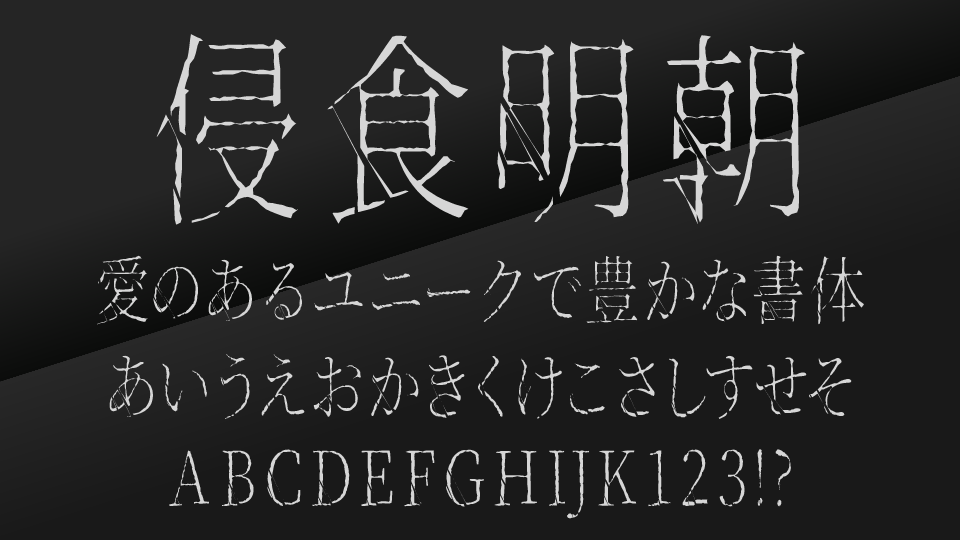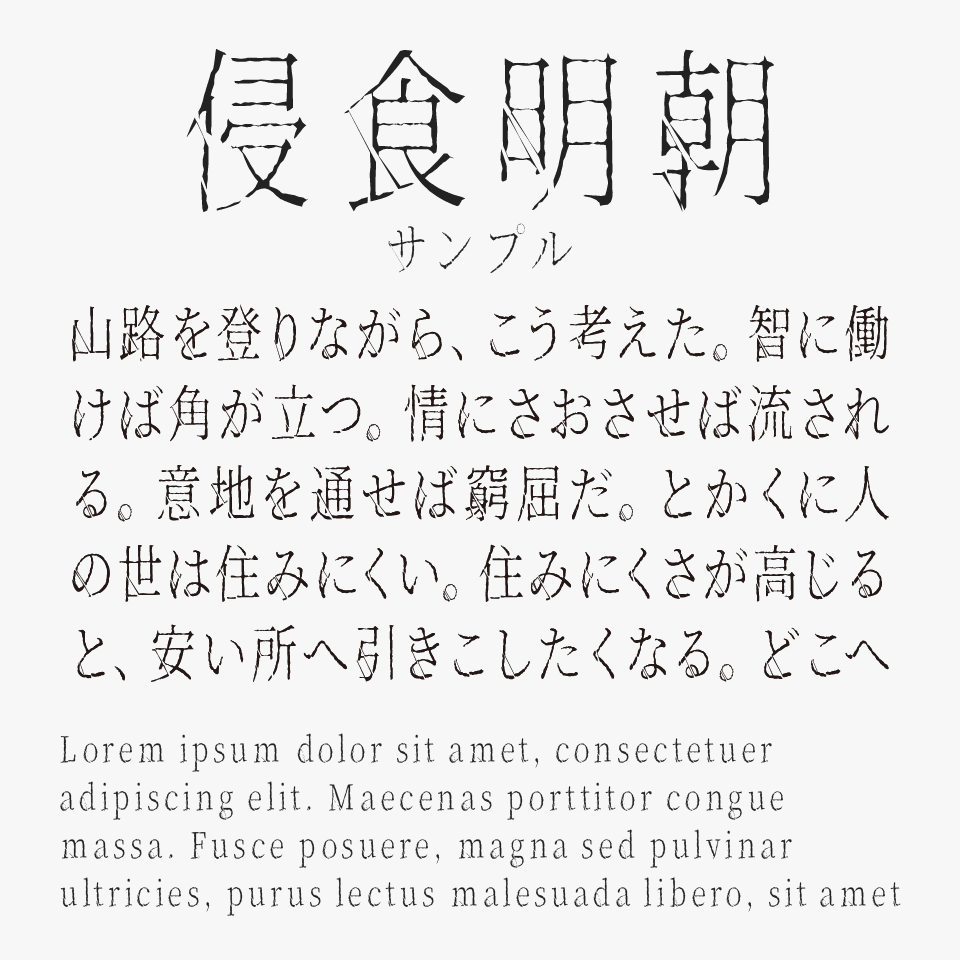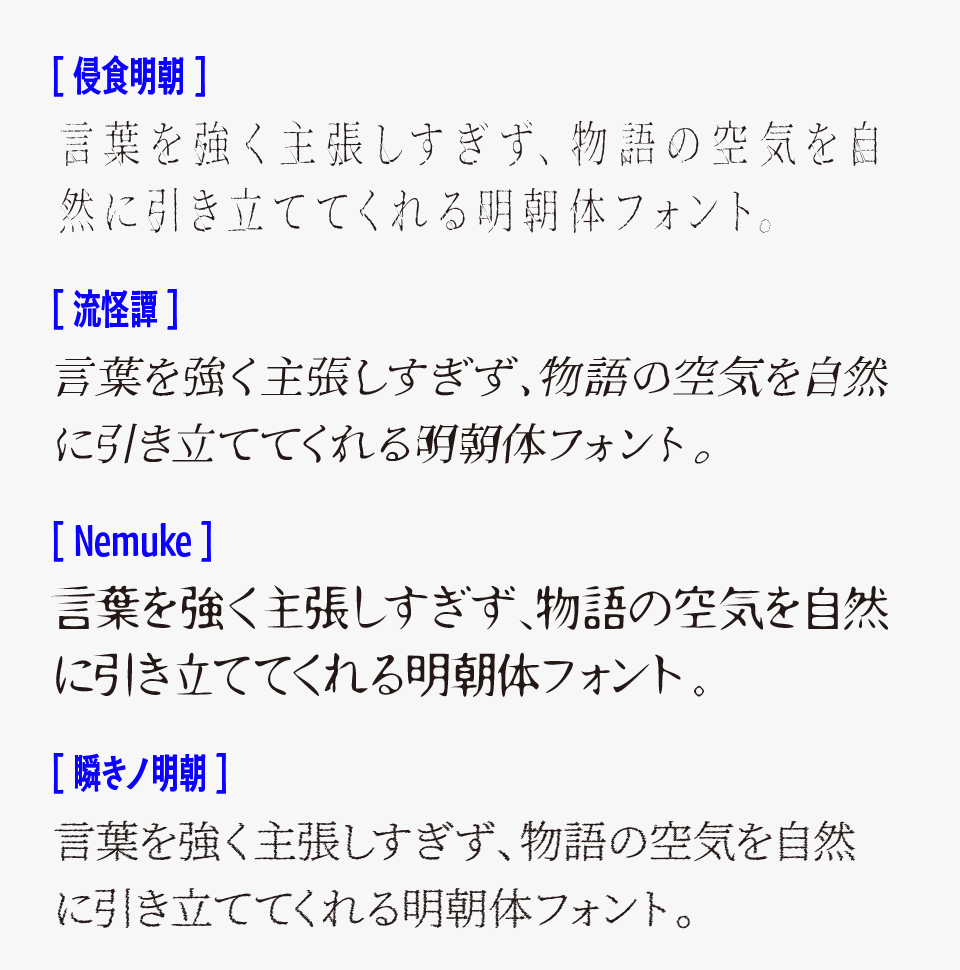
侵食明朝フォントは、源ノ明朝をベースに全体をやや長体に調整し、随所に亀裂を入れていることで、蝕まれて侵食されている雰囲気がある明朝体です。
繊細でシャープな骨格が持つ上品さと、侵食されたようなノイズ感が絶妙で、美しさの中に退廃的でダークな空気を感じられるフォントです。静かな恐怖感や異質さを演出できる、非常に個性の強い明朝体フォントです。
幻想的で不穏な世界観を演出しやすく、ホラー作品のタイトル、ゲームUI、ダークファンタジー系のビジュアル、小説表紙、MVデザインなどにぴったりなフォントです。
侵食明朝
侵食明朝フォントを、ほかの不穏さや異質感を表現した明朝体フォントと比較してみると、“文字そのものが侵食されていくような破壊的なデザイン表現”が特に印象的なフォントです。
比較フォントは、「流怪譚」「Nemuke」「瞬きノ明朝」を使用していますが、どれも特徴的な明朝体フォントなので、ぜひあわせてチェックしてみてください。